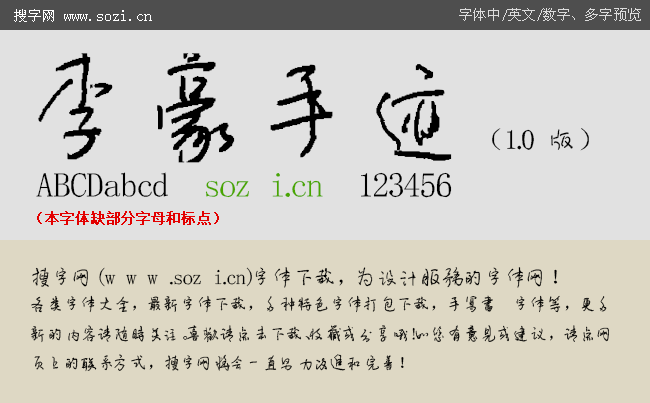
李豪手跡
搜字網(wǎng)提供一款李豪手跡中文書(shū)法字體下載,李豪手跡是一款手寫(xiě)風(fēng)格的鋼筆書(shū)法字體,字體書(shū)寫(xiě)流暢,字形大方,整體效果十分出色,適合應(yīng)用于廣告設(shè)計(jì)、名片設(shè)計(jì)、包裝印刷、產(chǎn)品設(shè)計(jì)等應(yīng)用。
- 風(fēng)格類(lèi)別: 手寫(xiě)書(shū)法體